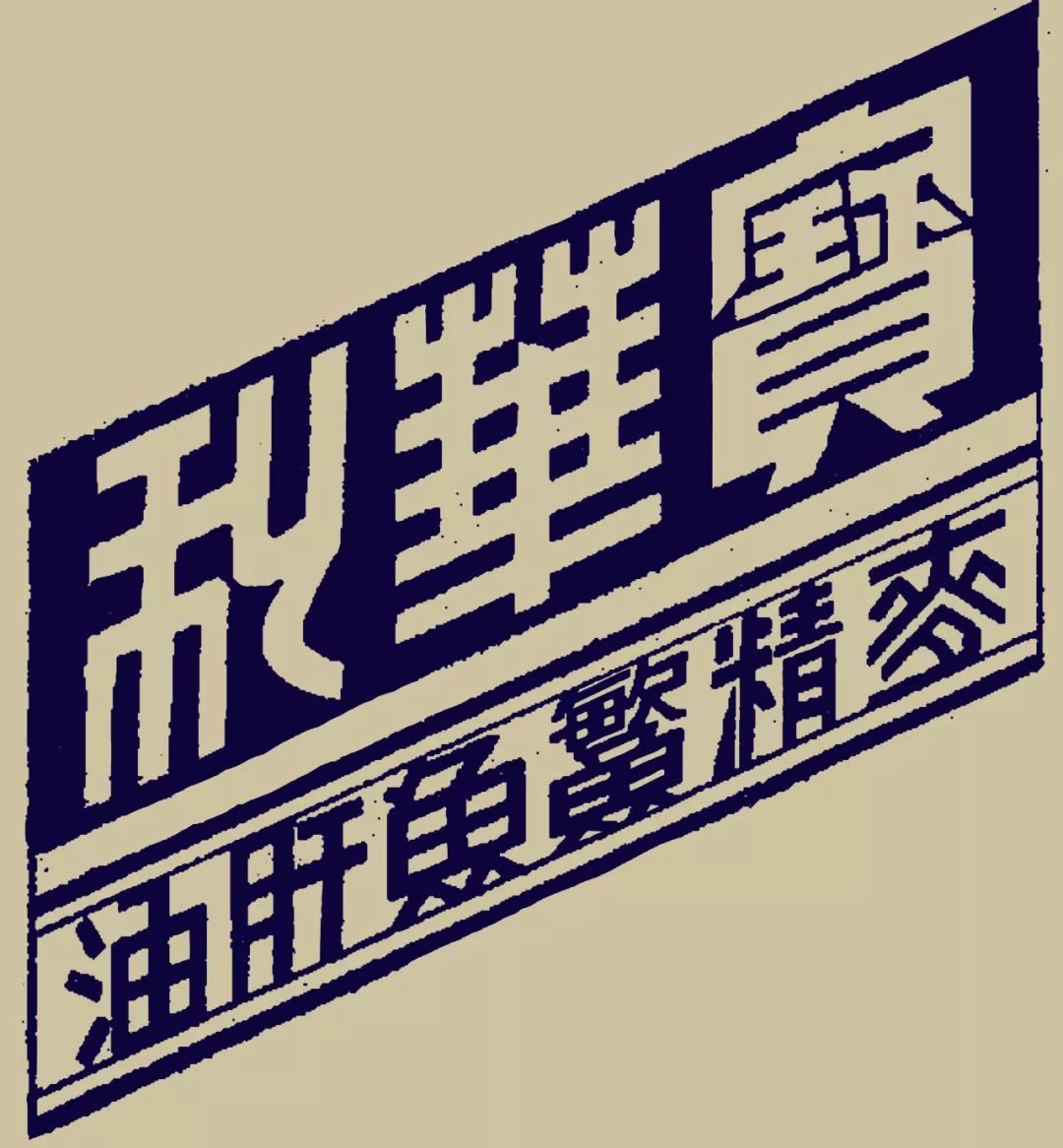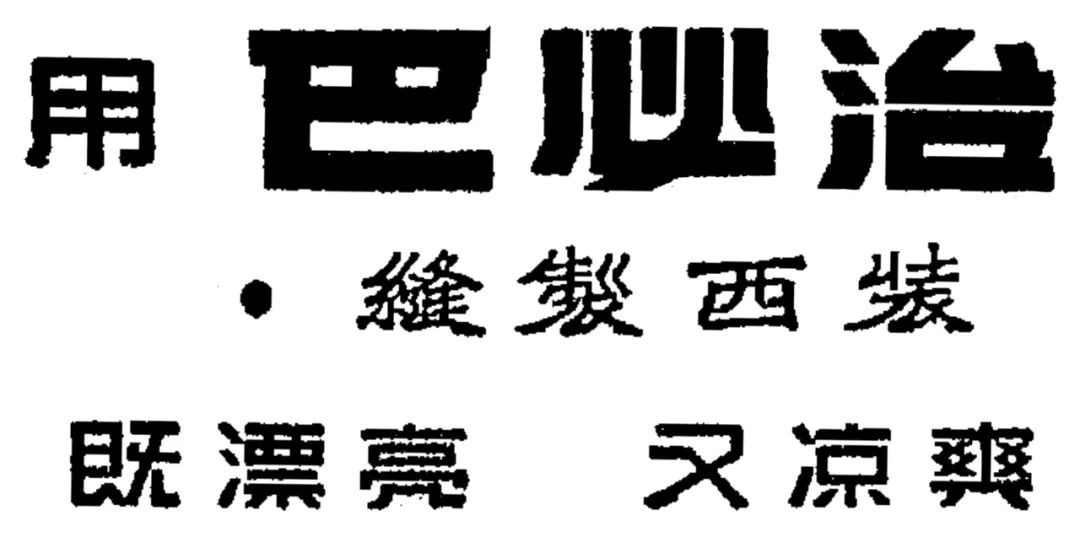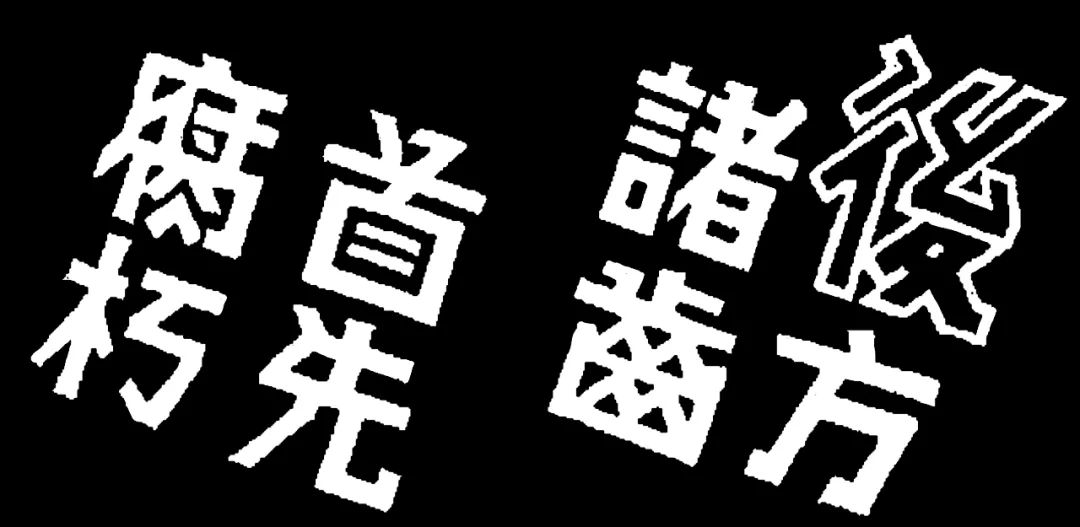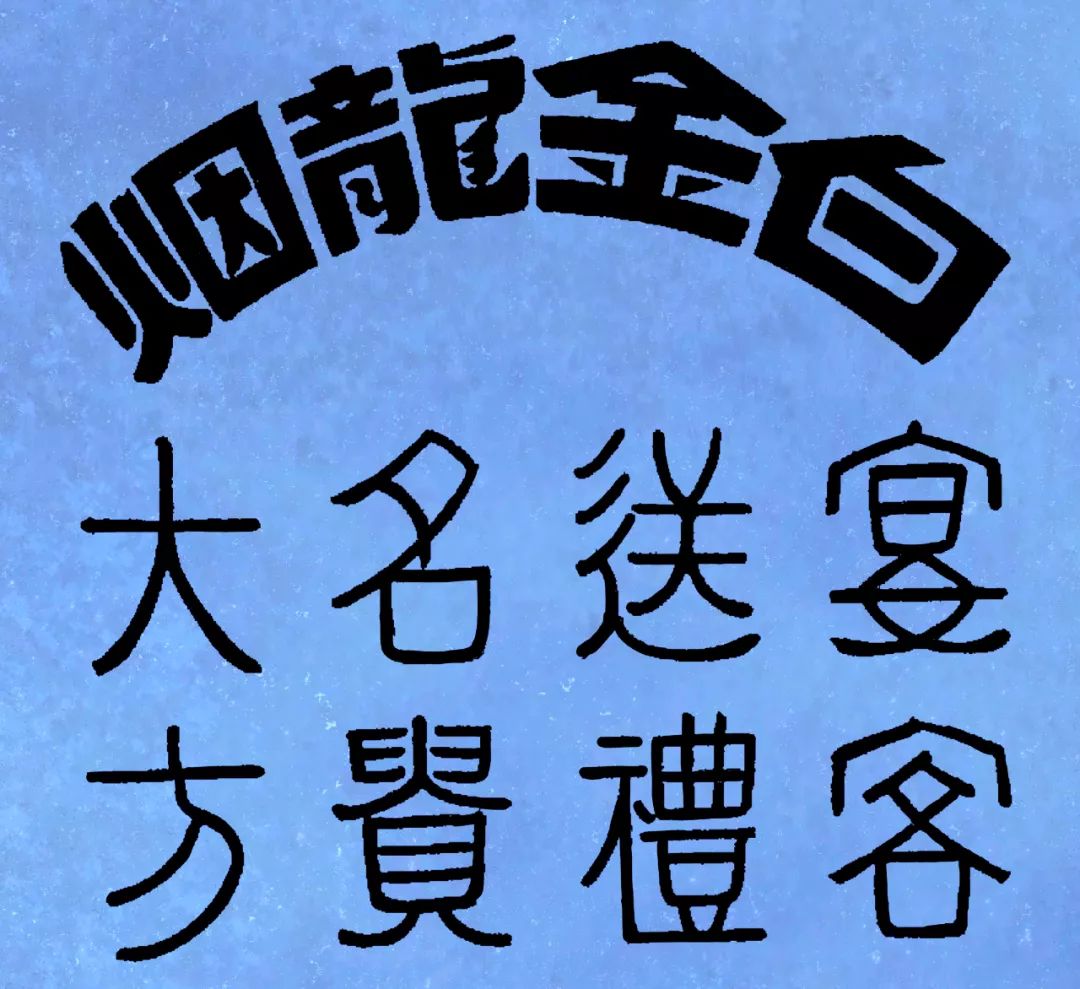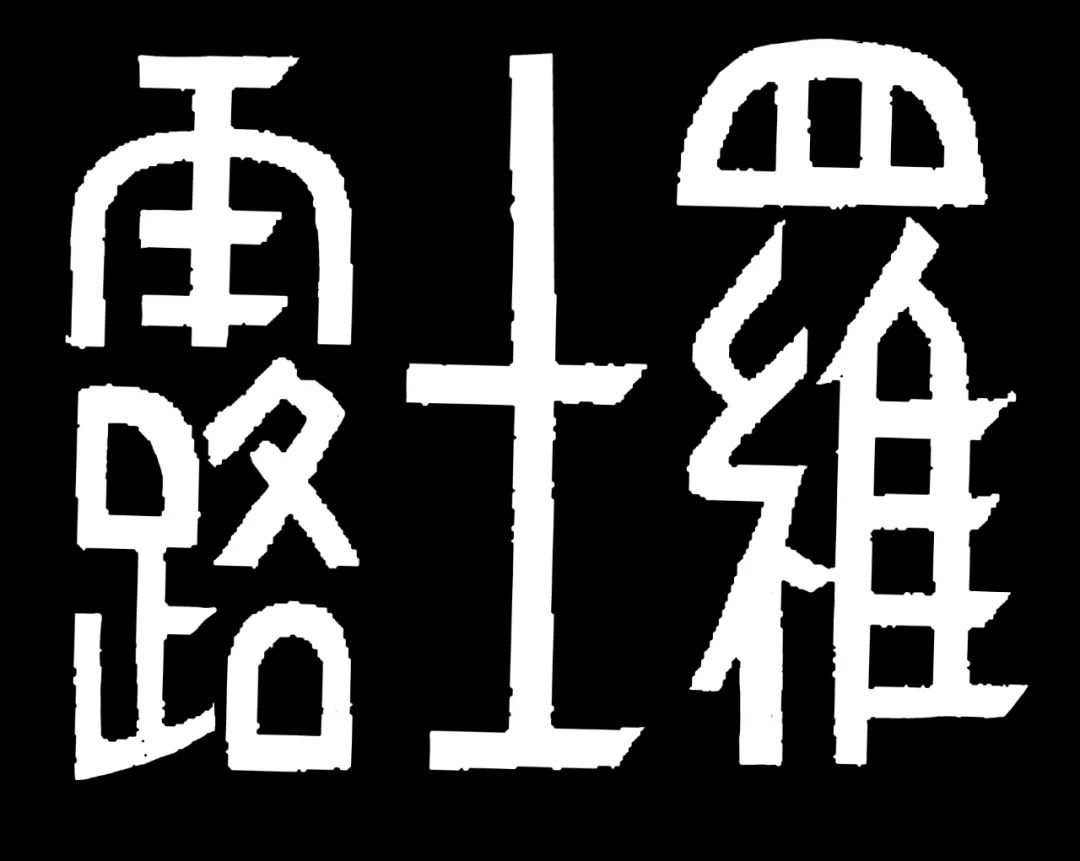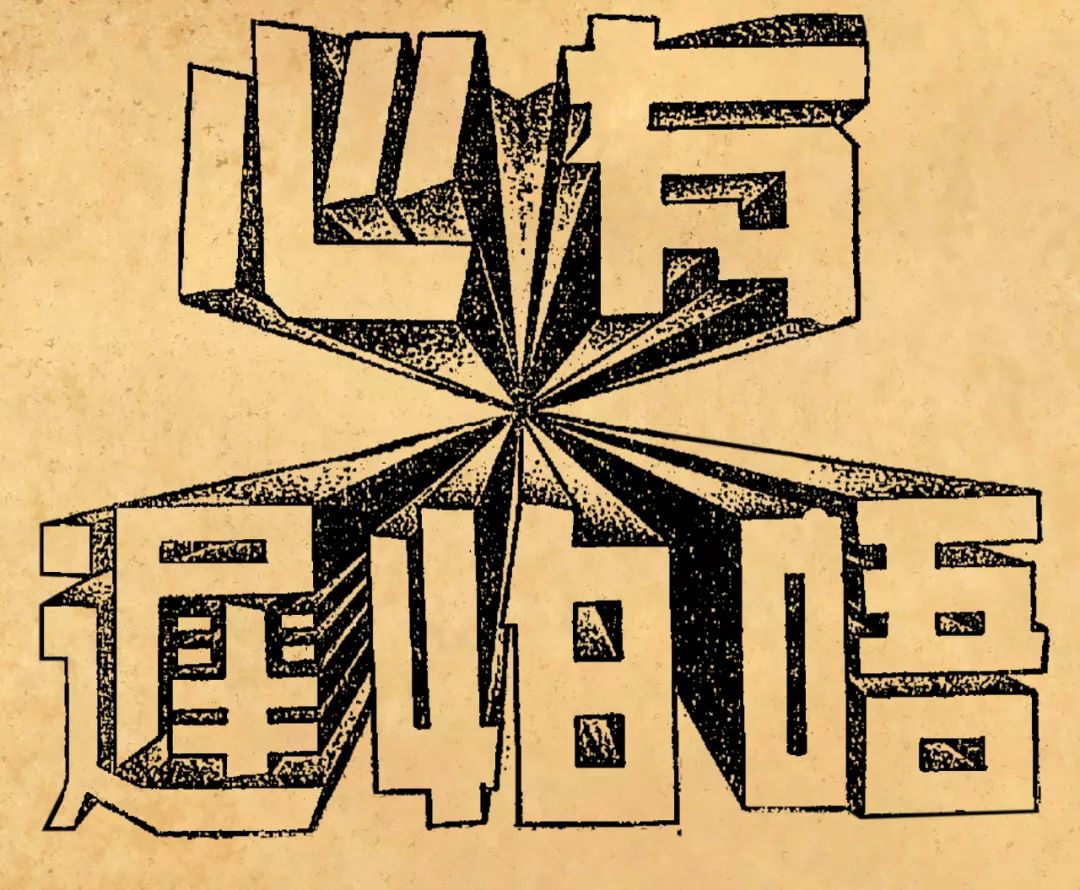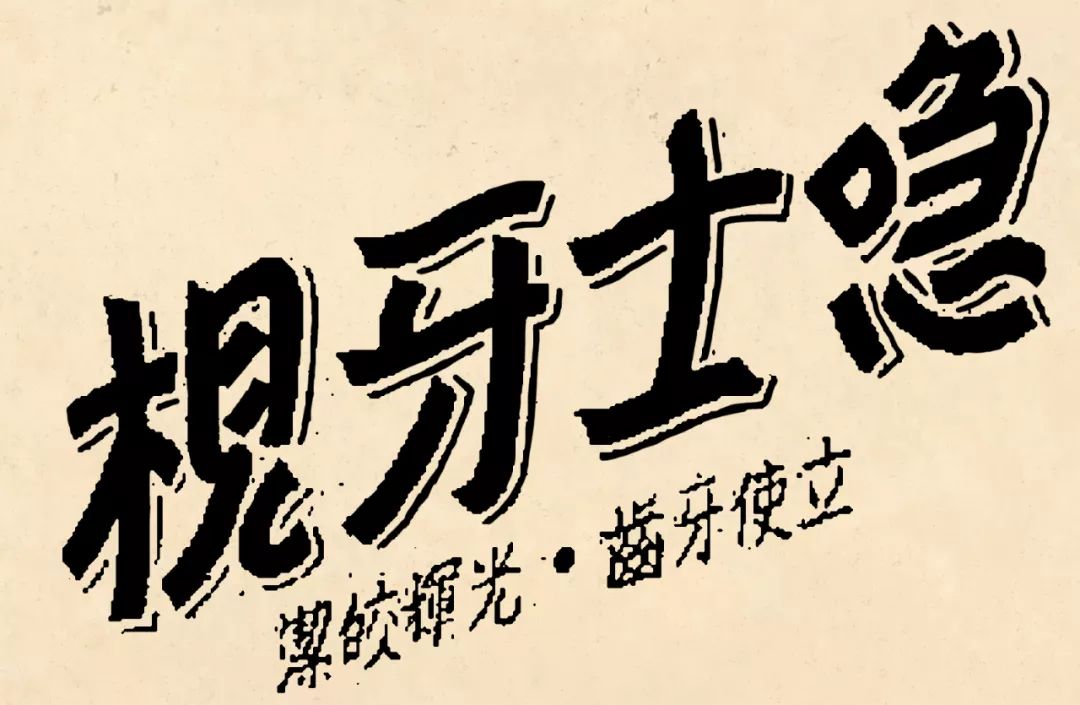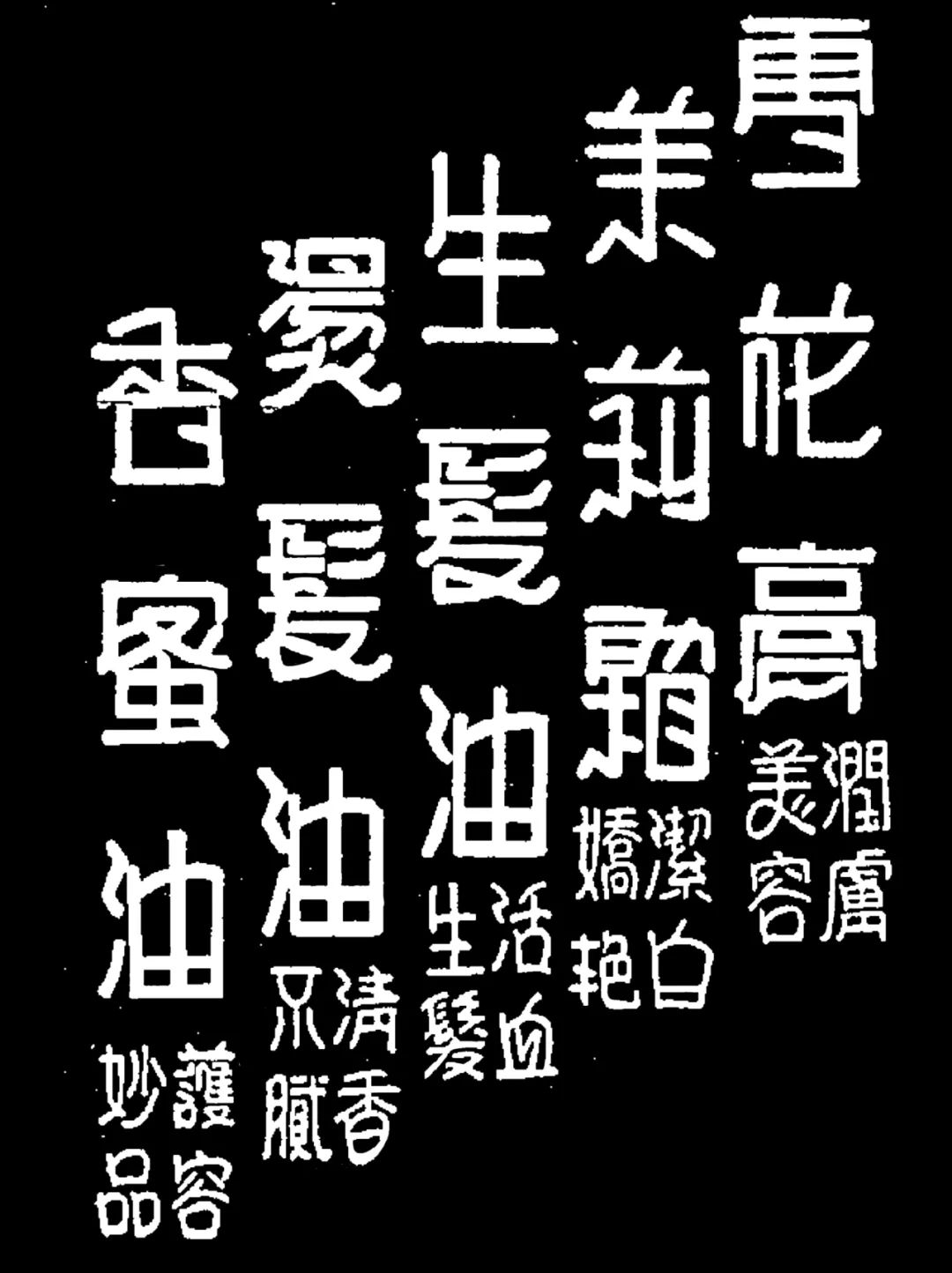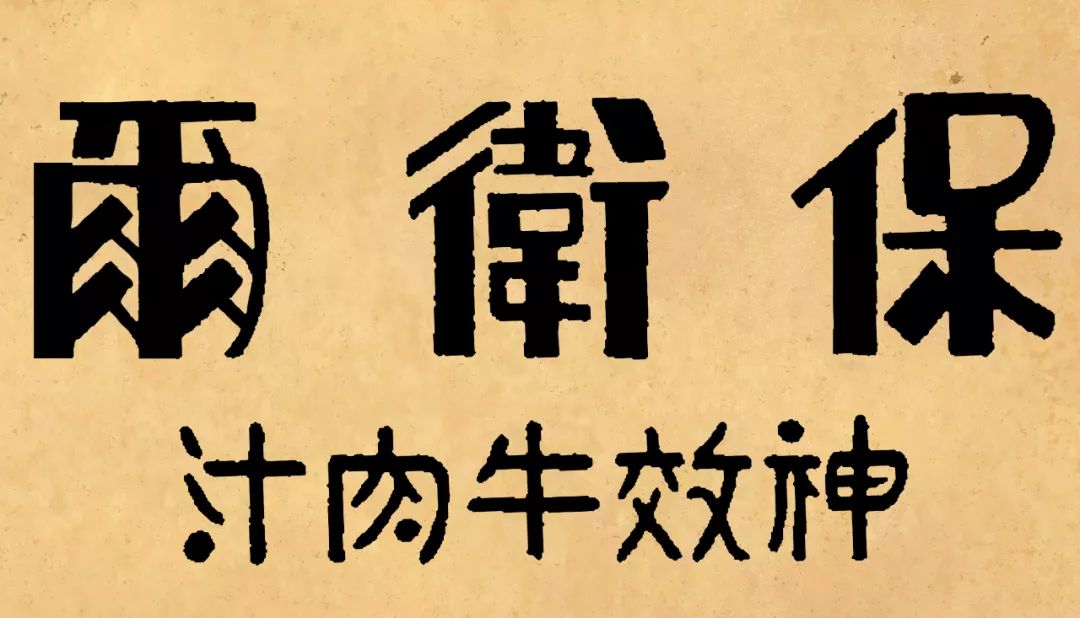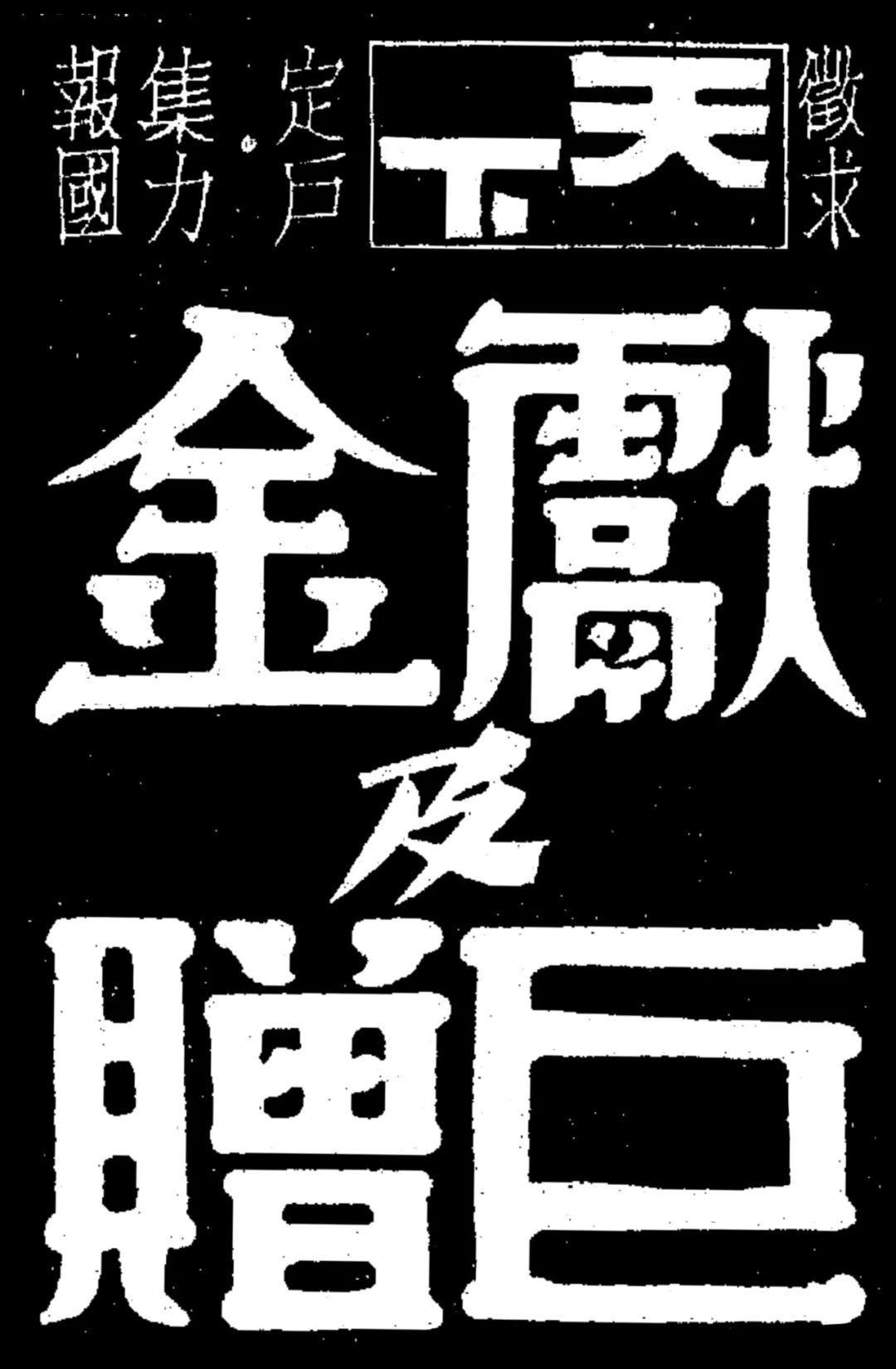
民国早期广告上的美术字
▲ 寶華利,麥精鰵魚肝油,華利兩字有些篆書體的味道
▲ 巴必治
▲ 後方諸齒,首先腐朽
▲ 眼科聖葯,篆書體和行書的融合
▲ 白金龍烟
▲ 朝氣蓬勃,精神暢旺,此字造型看起來很有精神,造型比較的反差
▲ 羅士露
▲ 有心唔怕遲
▲ 喼士牙梘
▲ 雪花膏、茉莉霜、生髮油、燙髮油、香蜜油,此字造型是基於行書體的美術字
▲ 保衛爾
▲ 徵求天下定戶集力報國獻金及巨贈,「獻金」、「巨贈」是基於隸書體的造型
▲ 金冠大酒樓夜總會,整體風格融合篆書體、行書的筆意
▲ 馬慈航個人繪畫展覽會,不設防城市(此字很有特色,全部是由三角組成的),九七四生肌白藥膏,咳葯中的良葯(類似篆書體的美術字)